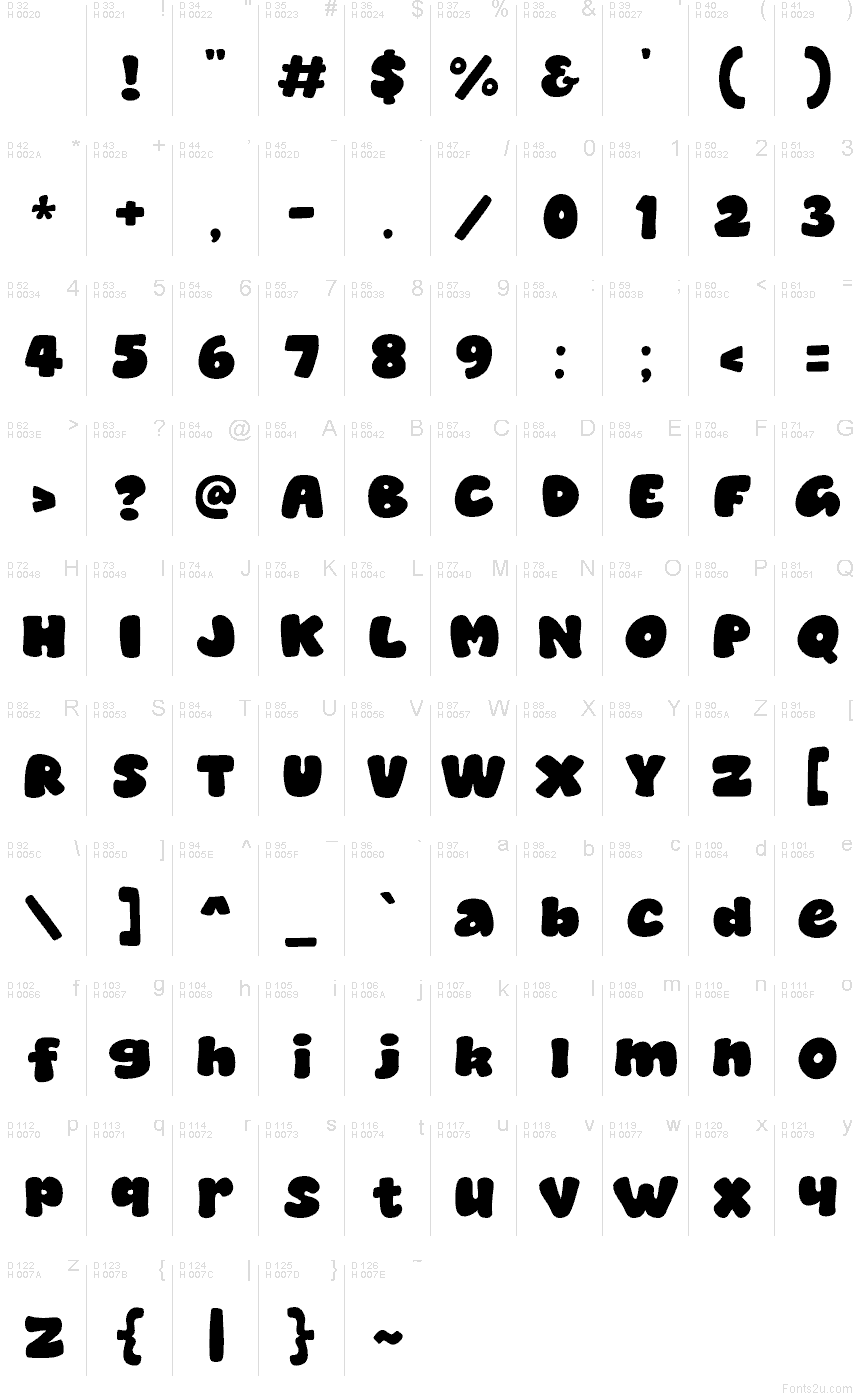
Salted Fries autorstwa MJType to darmowy krój pism o charakterze kreskówkowym, z pękatymi, miękko nieregularnymi literami. Jego szerokie pociągnięcia pędzla przechodzą w zaokrąglone kształty z małymi prześwitami i łagodnie ściętymi krawędziami, które przywodzą na myśl formy wycinane ręcznie. Sylwetka jest radosna i solidna, a nie uporządkowana czy geometryczna.
Opakowanie przekąski to wyjątkowo trafne zastosowanie dla tych sprężystych liter. Ich miękkie krzywe mogą również pasować do plakatów imprez dla dzieci, zabawnych gadżetów oraz identyfikacji wizualnej luźnych restauracji, w których słowa mogą nabrać przyjaznego charakteru ilustrowanej maskotki. Głównym odbiorcą są młode rodziny oraz wszyscy, których przyciągają jasne, humorystyczne grafiki spożywcze.